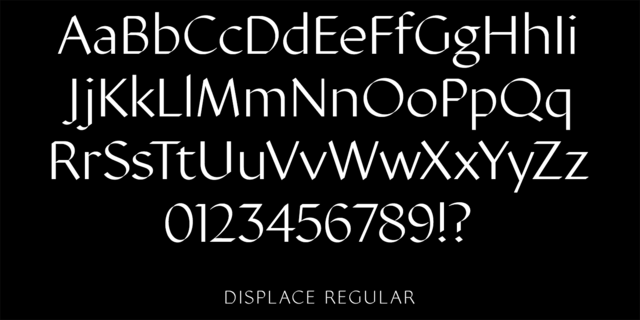
Displace 2.0 – это акцидентный шрифт без засечек. Оригинальный гуманистический гротеск, основанный на каллиграфическом дукте плоского пера. Шрифтовое семейство включает 5 начертаний: Light, Regular, Medium, Bold, Black. Шрифт разработал Денис Серебряков в 2019 году.
Ассоциации c начертанием Displace 2 BlackКачества и характер:
тяжелый, сильный, твердый, оригинальный, характерный, острый, резкий, четкий, серьезный, жесткий, железный, стальной, городской, устойчивый, необычный, гордый, динамичный, артистичный, дорогой, техничный, авторитетный, убедительный, важный, архитектурный, уверенный, броский, заметный, яркий, амбициозный, экспериментальный, активный, выразительный, элитный, качественный, серебрянный, драгоценный, отборный, богатый, звонкий, ровный, модный, современный, музыкальный, стеклянный, эстетский, пульсирующий, мерцающий